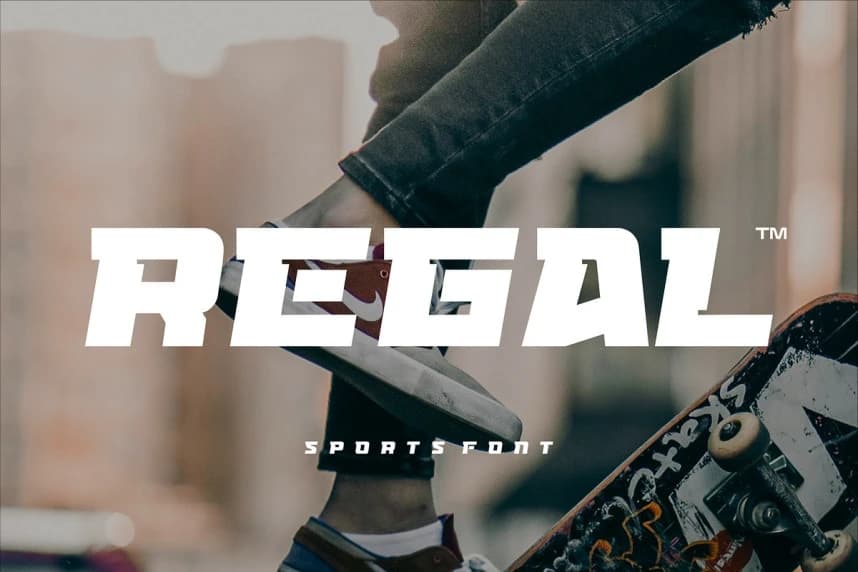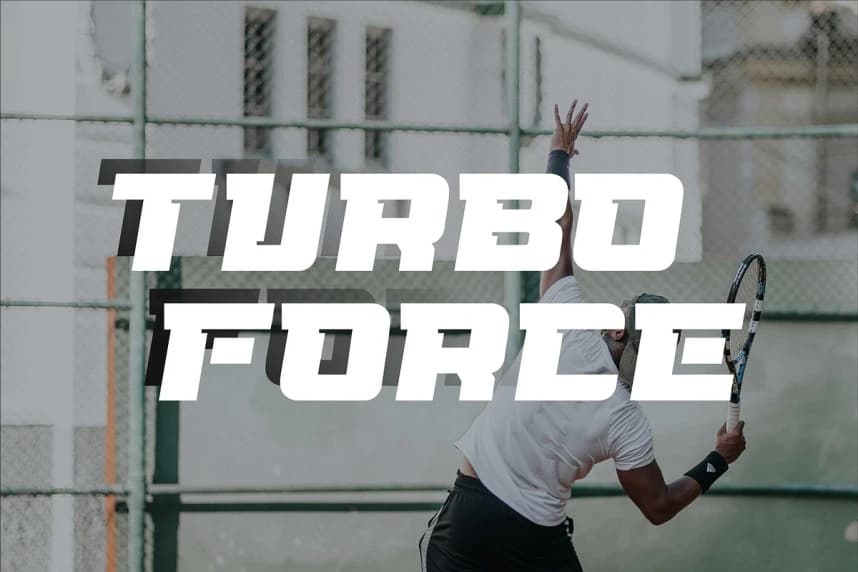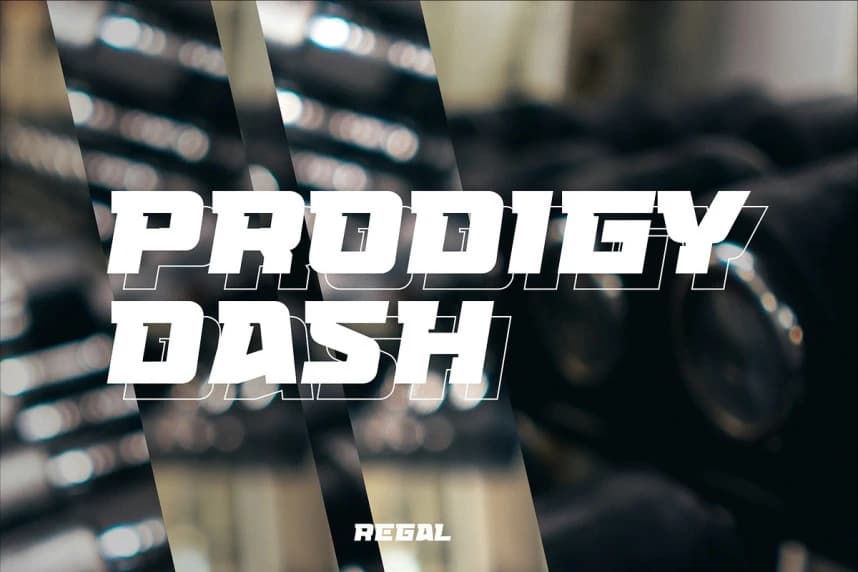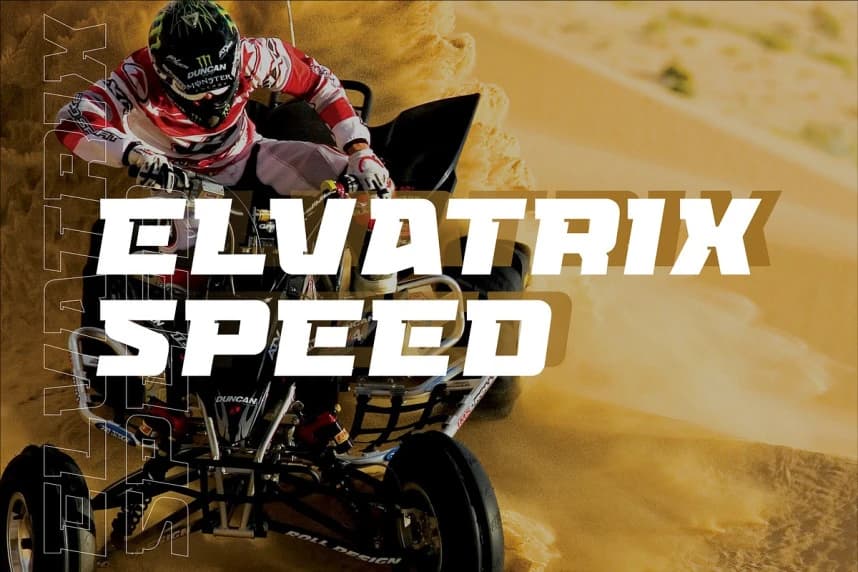
Regal Sport Font
REGAL SPORT Font, güç, hız ve etki için tasarlanmış cesur bir spor gösteri yazı tipidir. Keskin kenarları, sağlam oranları ve dinamik bir atletik stile sahip olan bu yazı tipi, spor markalaştırması, takım kimliği ve fitness ile ilgili tasarımlar için mükemmeldir. Güçlü karakter hatları, anında dikkat çeken etkili bir görsel varlık yaratır.